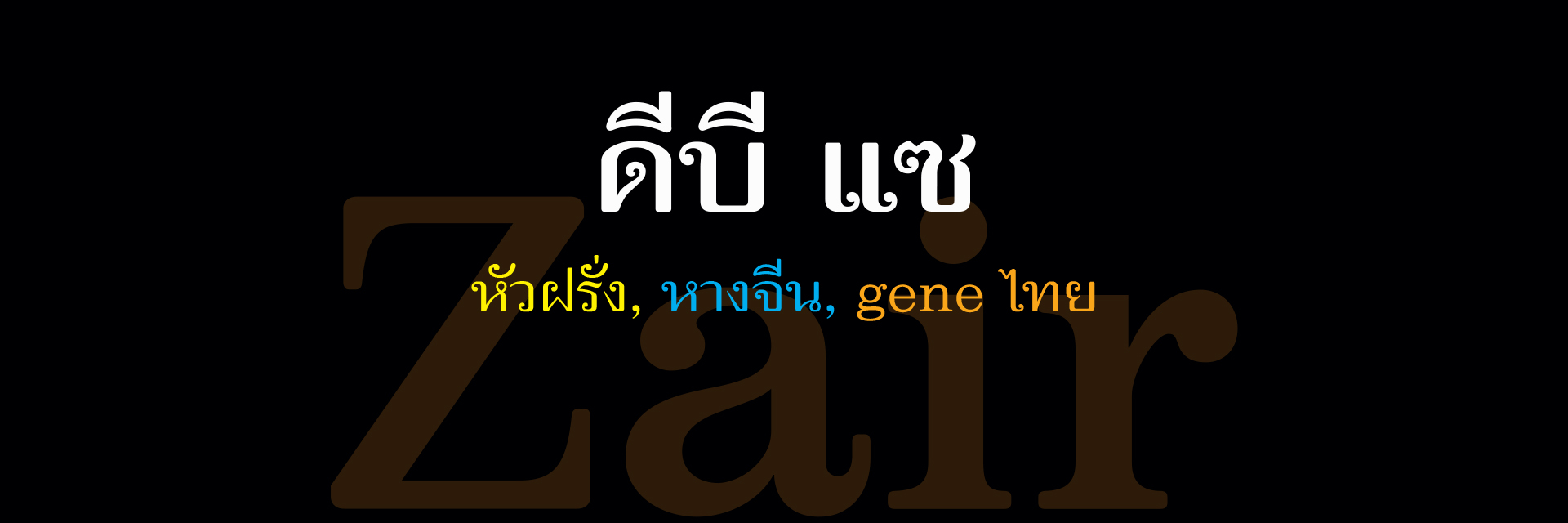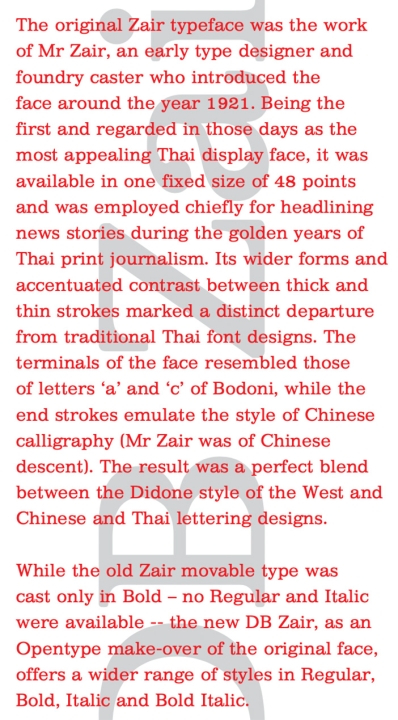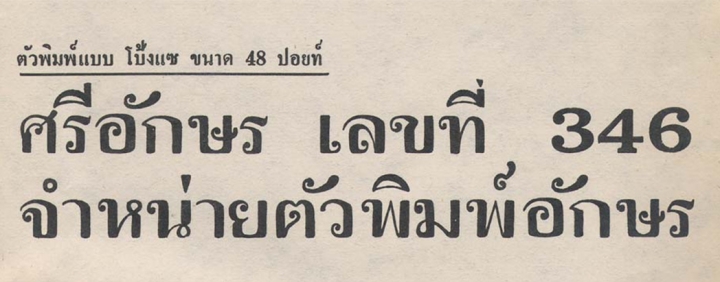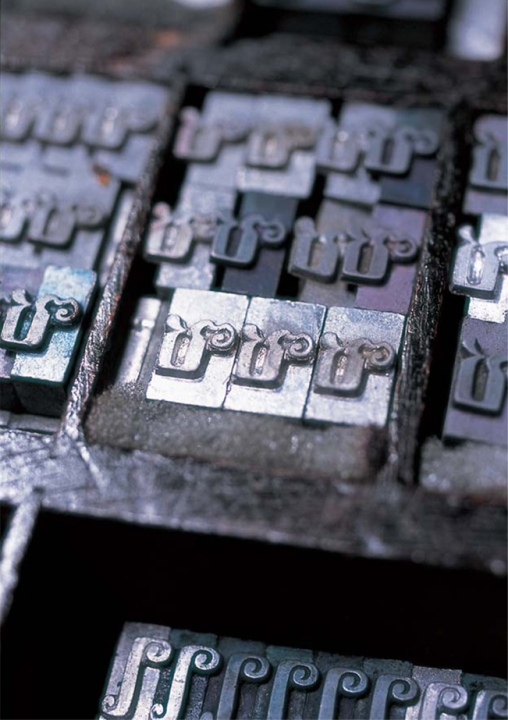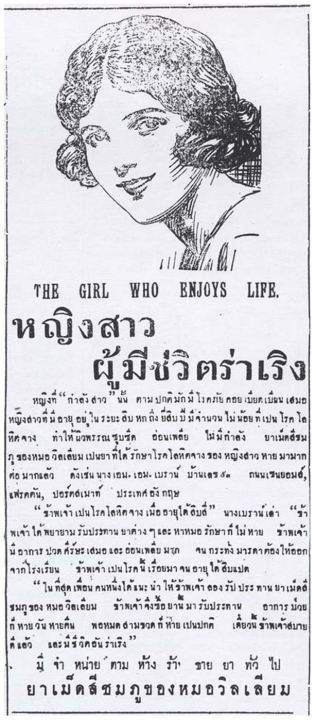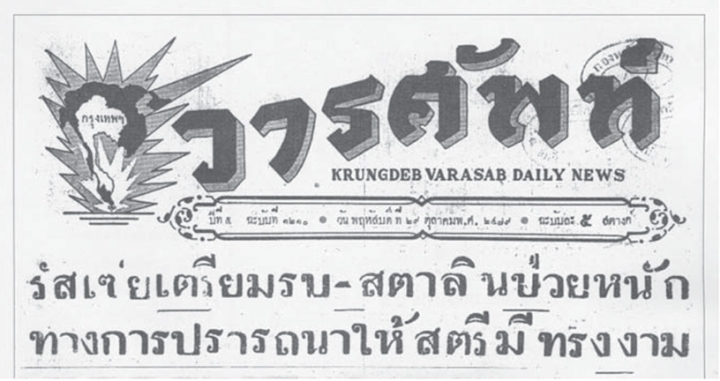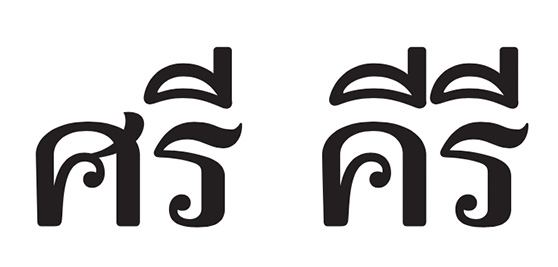
ในสมัยที่ไทยยังใช้ตัวเรียงพิมพ์ตะกั่วในงานสิ่งพิมพ์นั้น แบบตัวเรียงพิมพ์มักนิยมตั้งชื่อเรียกตามลักษณะของมัน เช่น ตัวบาง, ตัวกลาง (หมายถึงน้ําหนักเส้น), ตัวป้อม (หมายถึงความกว้าง), ตัวจิ๋ว, ตัวโป้ง (หมายถึงขนาด) เป็นต้น. ตามประวัติตัวโป้งของไทยถือกําเนิดขึ้นมาเพื่อรองรับยุคทองของหนังสือพิมพ์ไทยระหว่างสมัยรัชกาลที่ 6 - รัชกาลที่ 7. ตัวโป้งที่จัดว่าโป้งสมชื่อคือ ‘โป้งแซ’ เพราะ มีขนาดโตถึง 48 ปอยท์ มีปรากฏใช้งานเป็นหลักฐานตั้งแต่ ปี 2469 เป็นต้นมา จัดได้ว่า ‘โป้งแซ’ เป็นตัวพาดหัวตัวแรกในวงการพิมพ์ไทย (ตัวโป้งก่อนหน้านั้นเป็นเพียง “ตัวเนื้อที่โตขึ้นมาหน่อย” เท่านั้น), ต่อจากโป้งแซก็มี ‘โป้งใหม่’ ออกมาในปี พ.ศ.2472 และ ‘โป้งไม้’ ในปี พ.ศ.2480 ตาม ออกมา. ชื่อ ‘โป้งใหม่’ คงตั้งขึ้นเพื่อต้องการบอกว่าเป็นแบบใหม่กว่าโป้งแซ. ส่วนชื่อ ‘โป้งไม้’ ได้ชื่อเช่นนี้คงเป็น เพราะแรกเริ่มเป็นตัวเรียงขนาดโตที่ทําด้วยไม้ (Wooden type) ครั้นต่อมามีคนเอาไปทําเป็นตัวเรียงตะกั่วก็ยังคงเรียกติดปากว่าโป้งไม้เหมือนเดิม.
ทั้งโป้งแซ, โป้งใหม่, และโป้งไม้ ค่อยๆ เสื่อมความนิยมลงราวปลายยุคตัวเรียงตะกั่ว เพราะถูกแทนที่ด้วยอักษรช่างเขียนประดิษฐ์เอาไปทําบล็อคซึ่งดูตื่นเต้นไม่จําเจเหมือนตัวโป้งเดิมๆ โดยเฉพาะการเกิดของตัวอักษรลอกมากมาย นับแต่ปี พ.ศ.2516 เป็นต้นมา โดยยอดนักประดิษฐ์แบบตัวอักษรในยุคนั้น ถือเป็นการเพิ่มทางเลือกใหม่ๆ ในงานออกแบบสิ่งพิมพ์ ทําให้ตัวโป้งดูล้าสมัยไปเลยทีเดียว.
โป้งแซ ถ่ายจากหนังสือแบบตัวพิมพ์ของ ศรีอักษร ขนาดเท่าจริง
เมื่อเทคโนโลยีตัวพิมพ์เปลี่ยนจากตัวเรียงตะกั่วมาเป็น ตัวโฟโต้ (ที่คนไทยนิยมเรียกสั้นๆ ว่าตัวเรียงคอมพิว ตามชื่อบริษัท Compute Graphic ที่ทําธุรกิจให้บริการด้านนี้) ตัวโป้งใหม่ซึ่งดูเรียบง่ายกว่าโป้งแซและโป้งไม้ก็ได้รับการอนุรักษ์ไว้โดยอาจารย์มานพ ศรีสมพร ด้วยชื่อ ‘โกเมน’ ในปี พ.ศ.2519 กระทั่งปี พ.ศ.2532 ในช่วงต้นของฟอนต์ PostScript ‘โกเมน’ จึงกลายเป็น EAC Komain โดย อาจารย์มานพ อีกเช่นกัน และเพิ่มตัวหนาเข้าไป.
ในเวลาต่อมา โป้งไม้ ได้รับการอนุรักษ์เป็น PostScript ชื่อ SMB PongMai ใช้กับงานโฆษณาของ SC Matchbox ที่ต้องการแสดงความจริงจังและความจัง. อย่างไรก็ตาม แบบตัวอักษรโรมันทั้งใน EAC Komain และ SMB PongMai ก็ยังดูไม่กลมกลืนกับแบบตัวอักษรไทยเท่าที่ควร เมื่อมีการใช้คละในบรรทัดเดียวกัน
เวลาล่วงเลยมาจนถึงปี พ.ศ.2551 ซึ่งนับเป็นยุคเฟื่องฟูของฟอนต์ไทยแบบ Opentype โป้งแซจึงได้รับการอนุรักษ์ไว้ด้วยชื่อ DB Zair (อยู่ในฟอนต์ดีบี ชุดที่ 6) ด้วย ความเชื่อของผมว่าคุณค่าของโป้งแซยังรอการรื้อฟื้นกลับมาให้นักออกแบบรุ่นกลางและเก่าใช้เล่าเรื่องย้อนคุณค่าในอดีต รวมไปถึงให้นักออกแบบรุ่นใหม่ (ที่แม้ไม่เคยรู้จักโป้งแซมาก่อนก็ตาม) ต้องลุ่มหลงมีใจให้โดยไม่รู้ตัว.
โป้งแซ ใช้พาดหัวงานโฆษณาใน ศรีกรุง ฉบับวันจันทร์ที่ 14 กรกฎาคม 2473
จากการสังเกตของผม การที่โป้งแซสามารถสร้างปรากฏการณ์เป็นตัวพาดหัวยอดนิยมของตัวยุคตะกั่ว อาจตอบง่ายๆ ว่าเป็นเพราะโป้งแซเป็นตัวพาดหัวที่เกิดขึ้นเป็นตัวแรก หรือเป็นเพราะมันมีแบบตัวเรียงพาดหัวให้เลือกใช้ไม่มากก็ได้ แต่ถ้าลองพิจารณาให้ดีจะพบว่า โป้งแซมีอัตลักษณ์พิเศษที่แตกต่างจากตัวเรียงตะกั่วที่เกิดขึ้นก่อนหน้าหลายประการ จึงทําให้มันดีพอที่จะรักษาระยะเวลาของความนิยมได้นาน. กล่าวคือโป้งแซเป็นแบบตัวพิมพ์ตะกั่วชุดแรกที่มีสัดส่วนกว้าง, มีความเปรียบต่างระหว่างเส้นตั้งที่หนาและเส้นนอนที่บางอย่างเห็นได้ชัด, หัวอักษรคล้าย terminal ของตัว a ในฟอนต์ Bodoni, ส่วนหางอักษรที่ตวัดขึ้นลักษณะคล้ายเส้นพู่กันจีน (นายแซ เป็นช่างฝีมือ เชื้อสายจีน). แบบตัวเรียงโป้งแซจึงถือได้ว่าเป็นนวัตกรรมทางศิลปะที่เกิดจากการผสมผสานระหว่างรูปแบบตัวพิมพ์โรมันยุค Didone, รูปแบบตัวเขียนพู่กันจีน เข้ากับอักขระดั้งเดิมของไทยได้อย่างลงตัว. ศจ.กําธร สถิรกุล เคยเขียน ไว้ใน ‘ลายสือไทย ๗๐๐ ปี’ ว่าโป้งแซเป็นตัวพิมพ์สวยงาม ได้รับการยกย่องกันมากในยุคก่อน.
ในการอนุรักษ์โป้งแซ ผมต้องทําการศึกษาจากสิ่งพิมพ์เก่าๆ ทั้งจากต้นฉบับจริงและสําเนาที่คัดลอกย่อมาลงในหนังสือยุคหลัง. จะเห็นได้ชัดเจนถึงข้อดีของโป้งแซในการใช้เป็นตัวพาดหัวประการหนึ่ง คือ สระหน้า ไ ใ โ ค่อนข้างเตี้ยประหยัดที่. ปัญหาบางประการที่พบคือ ตัว ร มีขนาด แคบมาก ตอนเป็นตัวตะกั่ว ถ้าเรียงคําว่า ‘ศรี’ ไม่มีปัญหา แต่ถ้าเรียงคําว่า ‘คีรี’ สระอีตัวหลังจะชนตัวหน้า. ถ้าร่นสระ อี ตัวหลังไปทางขวา และร่น ร ตามออกไป ช่องไฟระหว่าง ค-ร จะหลวม. นี่เป็นปัญหาของตัวเรียงตะกั่ว ใน DB Zair ผมเพิ่มความกว้างตัว ร เล็กน้อย ขณะเดียวกันก็ใช้สระอีชุดพิเศษที่แคบลงเล็กน้อยช่วยด้วยอีกชั้นหนึ่งเพื่อแก้ปัญหาช่องไฟในภาพรวม. ตัว ง, ว ซึ่งจัดเป็นตัวแคบก็อาศัยชุด สระบน อิ อี อึ อื ที่แคบกว่าตัวปรกติช่วยเช่นกัน.
โป้งแซ ใช้พาดหัวข่าว วารศัพท์ ฉบับวันพฤหัสบดีที่ 29 ตุลาคม 2479
สระหน้าแบบโป้งแซ ออกแบบขึ้นมา เพื่อใช้เป็นตัวพาดหัว
DB Zair Bold ฟอนต์ Unicode เมื่อใช้กับโปรแกรมที่รองรับ Ligature จะมีชุดสระแคบพิเศษสําหรับตัวแคบ
ถ้าสังเกตเส้นล่างของอักษร บ, อ, ฯลฯ ในโป้งแซให้ดีจะพบว่ามุมด้านในบ้านกว่ามุมด้านนอก ลักษณะนี้ได้ถูกปรับแต่งใหม่ใน DB Zair ให้มุมโค้งสัมพันธ์กันมากขึ้น.
ส่วนตัวอักษรโรมันและตัวเลขอารบิกได้ดัดแปลงจากฟอนต์โรมัน 2 ฟอนต์ที่มีลักษณะใกล้เคียง Zair ผสมจนกลมกลืนกับ Zair อย่างที่เห็น. ในตอนแรกผมตั้งใจจะใช้ ชื่อว่า DB PongZair แต่เมื่อทําตัวปรกติเพิ่มเข้าไปแล้ว พบว่าใช้เป็นตัวพาดหัวรองได้สบายทั้ง 2 น้ําหนัก คําว่า ‘โป้ง’ จึงไม่จําเป็นอีกต่อไป คงเหลือแค่ ‘แซ’ คําเดียวพอ ตามชื่อผู้ออกแบบเพื่อเป็นการให้เกียรติท่าน นับเวลาแล้ว แซ ยุคดิจิตอลเกิดหลัง แซ ยุคตัวตะกั่วถึง 80 กว่าปี แต่ก็ ยังร่วมสมัยกับเมืองไทยยุคนี้ที่พูดไทยปนฝรั่งปนจีนอยู่.
เหมือนกับสไตล์ของ DB Zair ที่ยังคง ‘หัวฝรั่ง หางจีน gene ไทย’ ไว้ได้ครบ.